The Northern Block: Pennline Script und Selestin
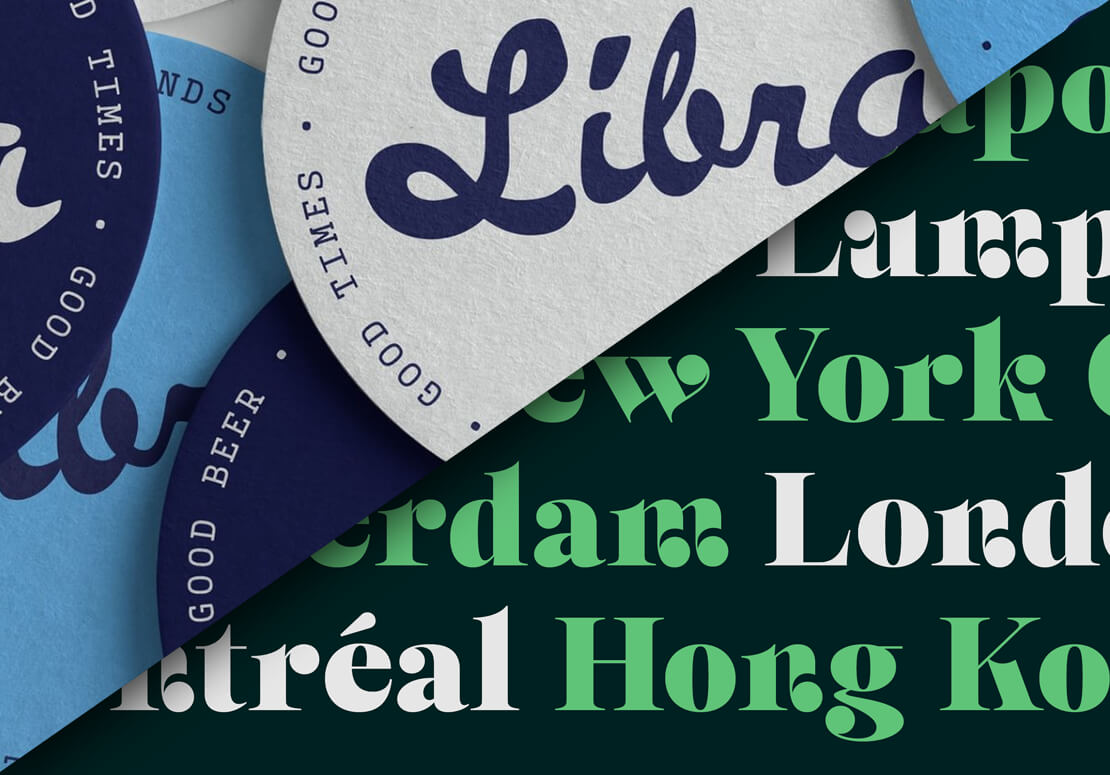
The Northern Block hat zwei neue Schriften veröffentlicht: Pennline Script und Selestin. Beide Families werden auf der Website der Type-Foundry mit Hintergrundinfos, PDF-Specimen und Testfonts vorgestellt.
Schwungvolle Pennline Script
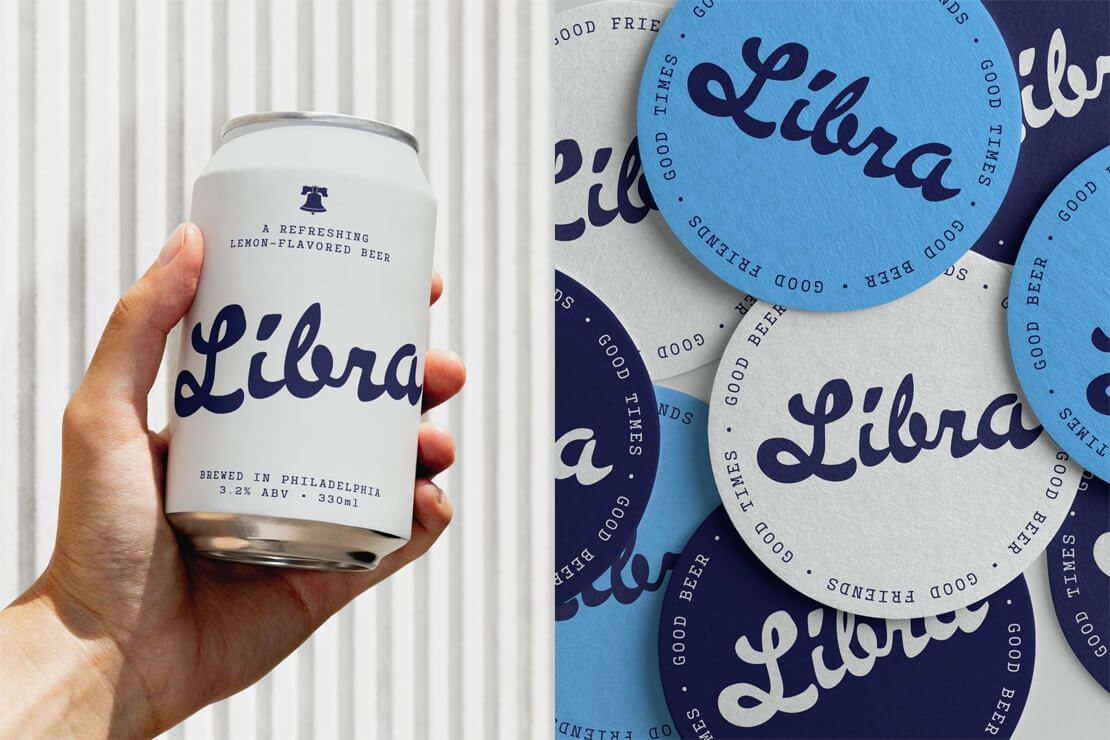
Pennline Script ist eine digitalisierte Wiederbelebung von Bulletin, die 1899 von der Keystone Type Foundry in Philadelphia (Pennsylvania, USA) gegossen wurde. Die Script-Schrift orientiert sich an amerikanischem Handlettering und greift eine lebhafte, brush-inspirierte Anmutung auf. Dabei wurden alle Glyphen neu gezeichnet und in der Balance angepasst, um die unregelmäßige Ausdruckskraft des Originals zu erhalten und zugleich eine zeitgemäße Nutzung zu ermöglichen.
Im Einsatz ist Pennline Script vor allem dort naheliegend, wo Texte eine handschriftliche Note und Eigencharakter bekommen sollen – beispielsweise in Headlines, Packaging oder Editorial-Anwendungen. Der Vintage-Look kann zudem gezielt für nostalgische Anmutungen genutzt werden.
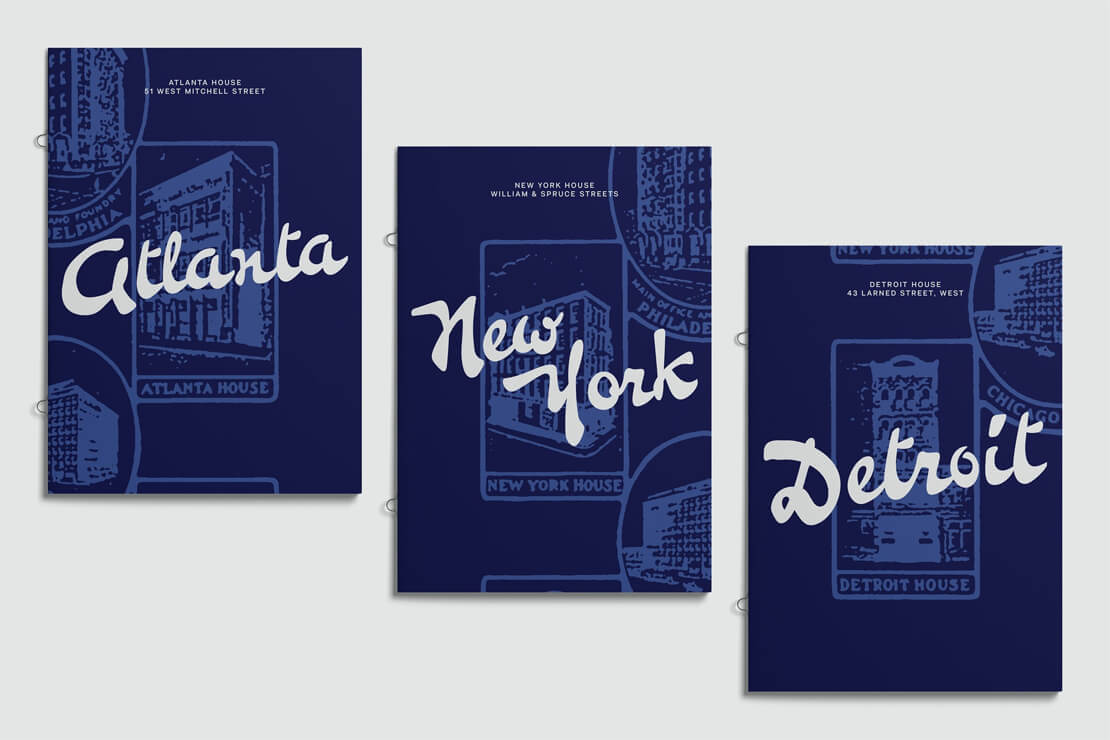
- Family: Complete Family (1 Font)
- Umfang: über 1.050 Zeichen
- Unterstützung für viele Sprachen
- OpenType-Features: kontextabhängige Alternativen, Ligaturen, Initialen, 8 Stylistic Sets
Selestin Display-Schriftfamilie
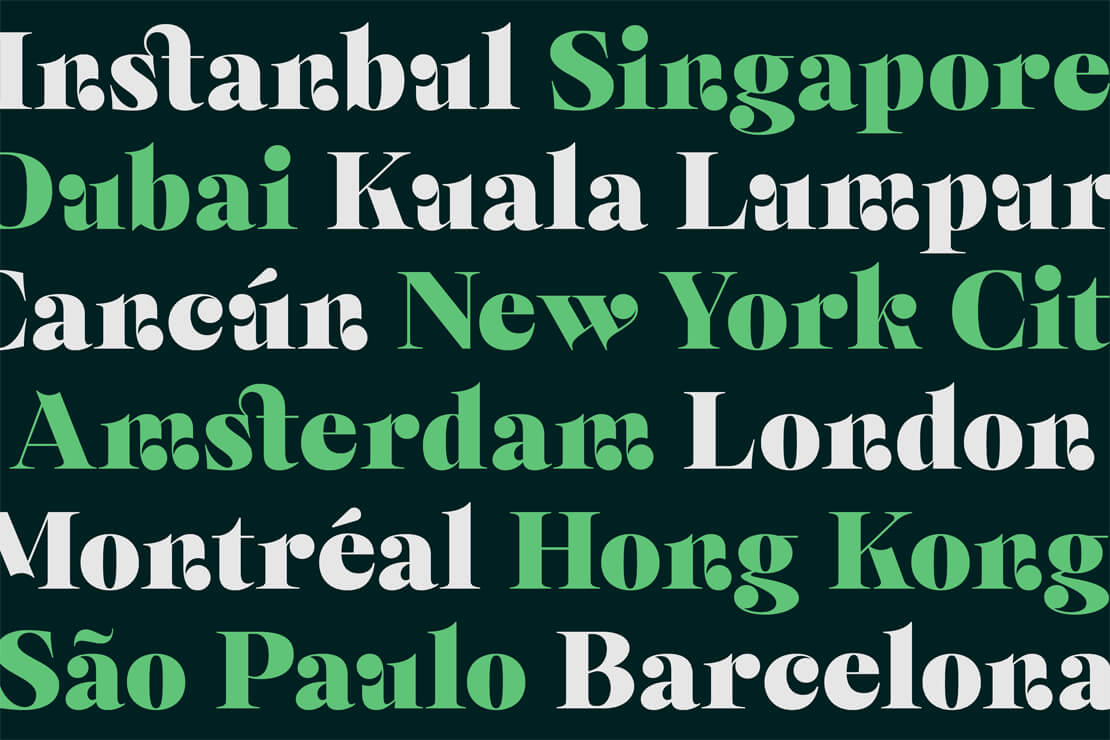
Selestin ist eine kontrastreiche Display-Serif, die kalligrafische Einflüsse mit der Präzision gravierter Typografie verbindet. Auffällig sind Ball Terminals, feine Serifen und eine deutliche Strichmodulation. Als Referenzen nennt The Northern Block unter anderem Broad-Nib-Kalligrafie, gravierte Typografie des 18. Jahrhunderts sowie Art-Nouveau-Ornamentik.
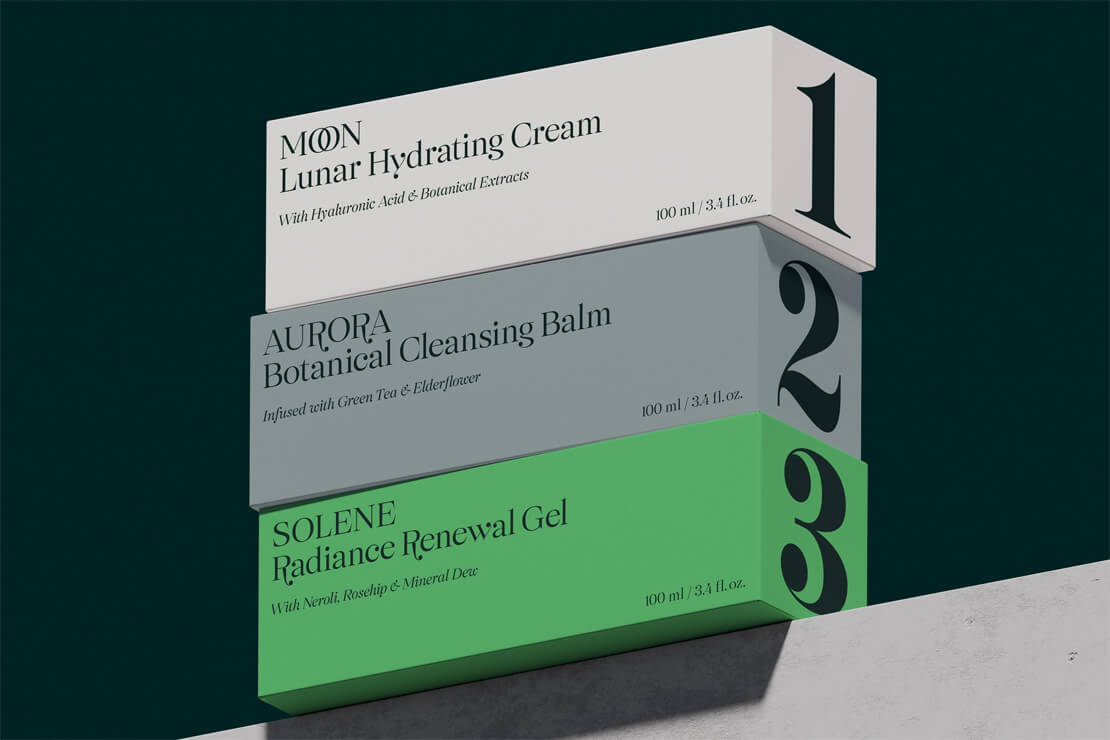
Die Schriftfamilie zielt bewusst auf Anwendungen, in denen Serif-Schriften als prägende Elemente eingesetzt werden – beispielsweise in Editorial-Layouts, Branding im Premium-Umfeld oder auch beim hochwertigen Packaging-Design.
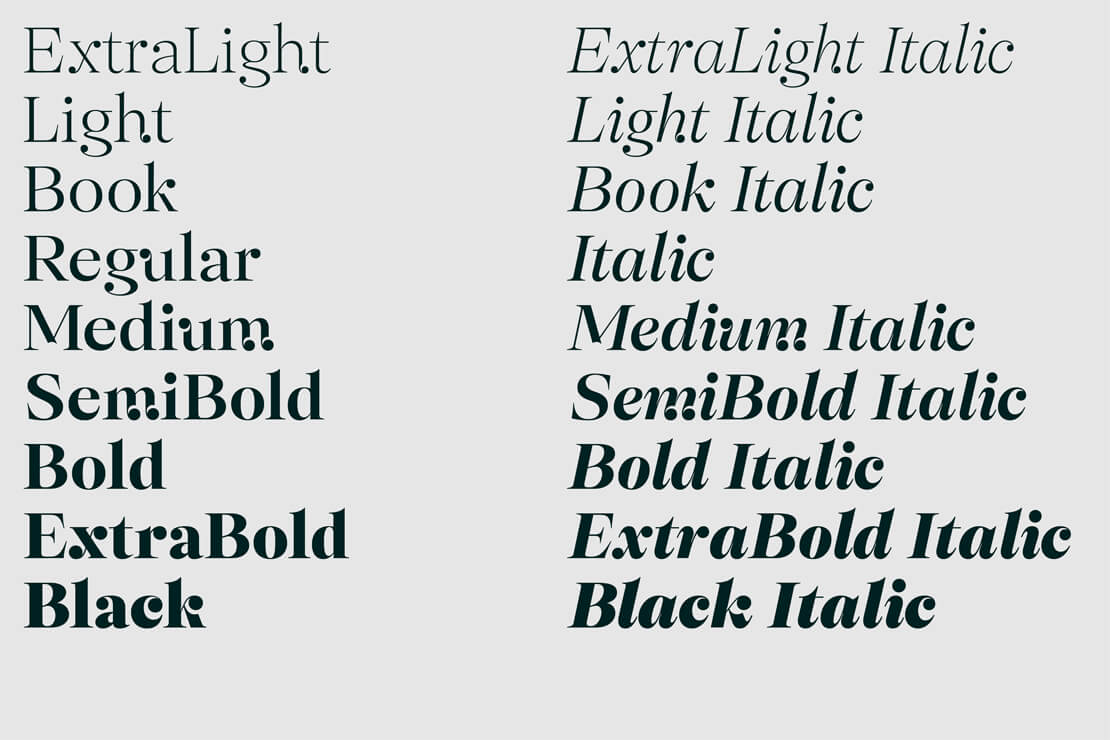
- Family: Complete Family (18 Fonts)
- Umfang: 681 Zeichen pro Schnitt
- Umfangreiche Sprach-Unterstützung
- OpenType-Features: kontextabhängige Alternativen, Ligaturen, Formen etc.
- Weitere Features: Case-sensitive forms, 14 Stylistic Sets